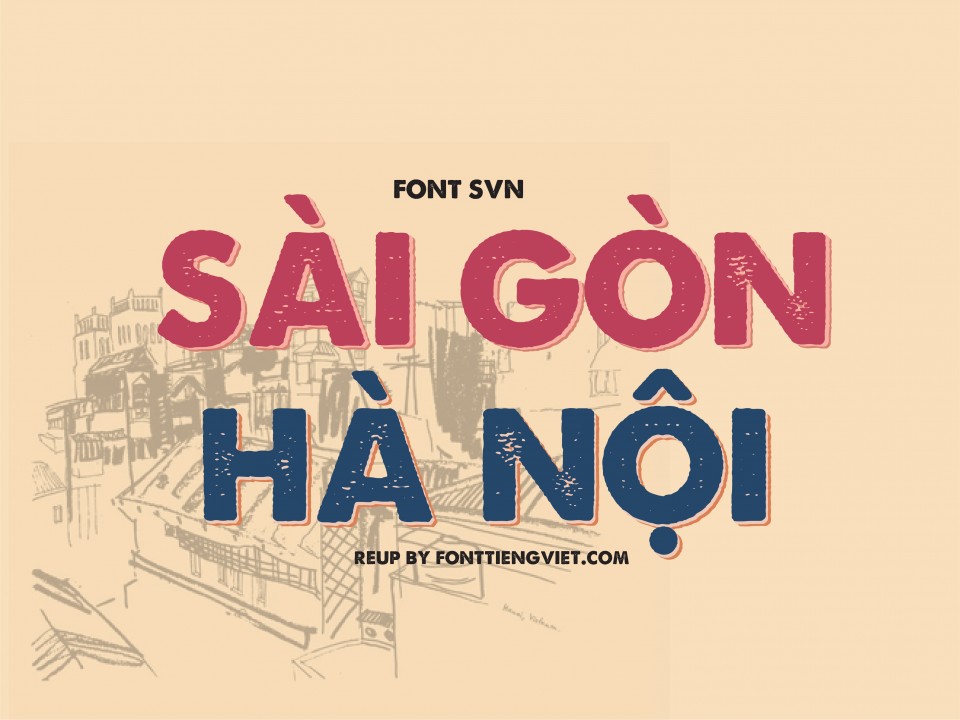
Giới thiệu về Font việt hóa SVN A Love Of Thunder
Trong thế giới thiết kế đồ họa chuyên nghiệp, việc lựa chọn một Font Chữ phù hợp đóng vai trò then chốt trong việc truyền tải thông điệp. Font việt hóa SVN A Love Of Thunder là một trong những bộ phông chữ độc đáo, mang phong cách mạnh mẽ nhưng không kém phần nghệ thuật. Được Việt hóa bởi đội ngũ SVN, bộ font này giúp người dùng dễ dàng sử dụng tiếng Việt mà không lo lỗi hiển thị, đặc biệt phù hợp cho các dự án sáng tạo từ học đường đến truyền thông.
Đặc điểm nổi bật của bộ font
Bộ font này gây ấn tượng mạnh nhờ những đường nét dày dặn, mô phỏng phong cách truyện tranh và phong cách cổ điển đầy cá tính. Các ký tự được chăm chút tỉ mỉ, tạo nên sự cân đối và dễ nhìn ngay cả khi hiển thị ở kích thước nhỏ. Điểm cộng lớn nhất của Font việt hóa SVN A Love Of Thunder chính là khả năng ứng dụng linh hoạt, giúp các bạn học sinh, sinh viên tạo nên những bài thuyết trình hay báo cáo học tập vô cùng sinh động và bắt mắt.
Ứng dụng Font việt hóa SVN A Love Of Thunder trong thiết kế
Nhờ tính thẩm mỹ cao, bộ font này thường xuyên được ưu tiên sử dụng trong các sản phẩm thiết kế bìa sách, poster sự kiện và logo thương hiệu. Khối lượng chữ rõ ràng giúp người xem dễ dàng ghi nhớ thông tin ngay từ cái nhìn đầu tiên. Ngoài ra, phông chữ này còn rất được ưa chuộng trong việc tạo các tiêu đề nổi bật cho video hoặc hình ảnh trên mạng xã hội, mang lại cảm giác chuyên nghiệp và hiện đại cho sản phẩm sáng tạo.
Lưu ý khi sử dụng
Mặc dù bộ font mang phong cách phá cách, người dùng nên kết hợp khéo léo với các font chữ không chân khác để tạo sự hài hòa. Việc sử dụng đúng ngữ cảnh sẽ giúp nội dung của bạn trở nên nổi bật và tinh tế hơn bao giờ hết.